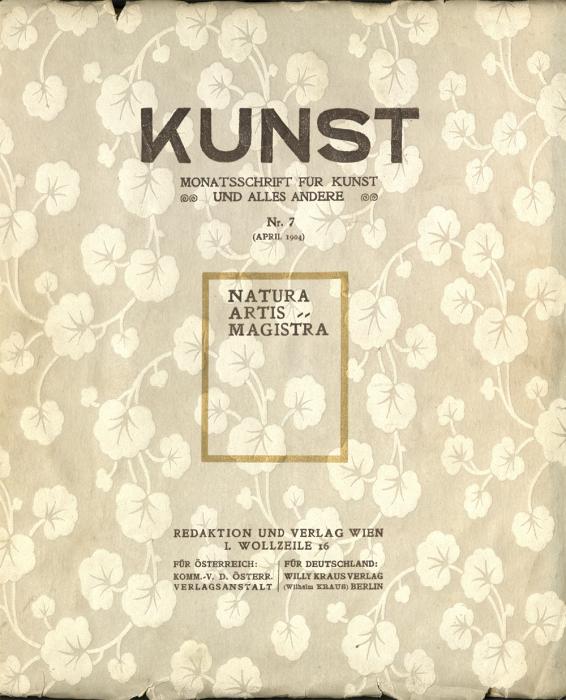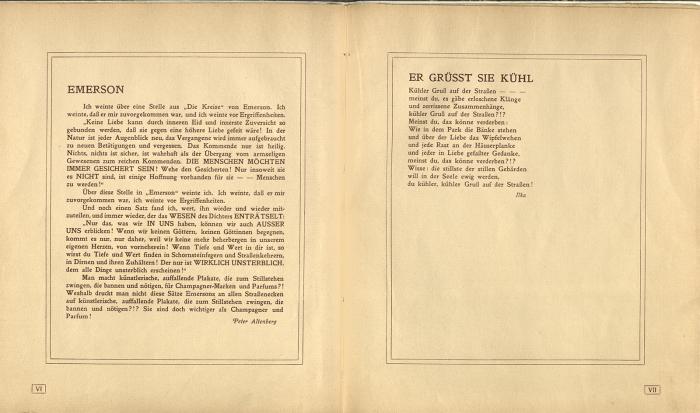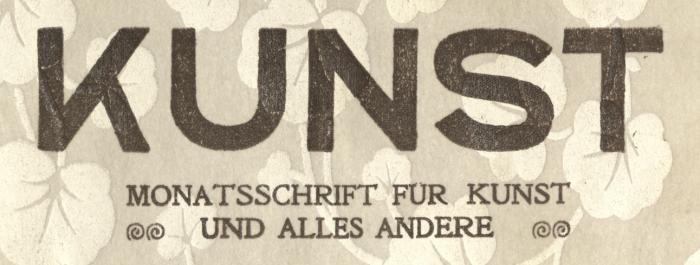
Schriftart KUNST
Weiss jemand, um welche Schrift es sich bei untenstehendem "KUNST"-Schriftzug handelt? (Stammt von einer Wiener Kunstzeitschrift, 1903/1904.) Ich glaube, die Schrift des Untertitels ist eine Garamond? Gibt es ausserdem eine typographische Bezeichnung für diese spiral- bzw. schneckenförmigen Verzierungen links und rechts?
Weiss jemand, um welche Schrift es sich bei untenstehendem "KUNST"-Schriftzug handelt?
Das ist handgemacht. K und S sind derart verunglückt, daß kaum vorstellbar ist, daß eine Gießerei das als Satzschrift produziert hätte. Wenn ich mir den Hintergrund ansehe, tippe ich auf Linol- oder Holzschnitt oder ein ähnliches Verfahren.
Ich glaube, die Schrift des Untertitels ist eine Garamond?
Eher nicht, und wenn, dann eine ganz schlechte. Bei einigen Buchstaben passen die Proportionen gar nicht zur Garamond. Vielleicht ist das auch eine händisch nachgezeichnete oder nachgeschnittene Schrift nach einer Garamond-Vorlage.
Gibt es ausserdem eine typographische Bezeichnung für diese spiral- bzw. schneckenförmigen Verzierungen links und rechts?
Ganz allgemein: Schmuck. Eine konkrete Bezeichnung für diese Form wird es nicht gegeben haben.
Auch wenn ich dem Kollegen Pachulke nur ungern widerspreche: KUNST könnte schon eine Satzschrift sein, so eine jugendstilige (bzw. Art Deco-)-Serifenlose aus der Jahrhundertwende, die in Österreich und auch in Deutschland, Italien, Frankreich damals echt gern genommen wurden. "Secession" oder Secessionsgrotesk hieß mal eine derartige Schrift, wenn ich mich richtig erinnere. Es dürfte einige ähnliche und vielleicht sogar sehr ähnliche digitale Schriften geben ... suche einfach mal unter den Stichworten Art Deco, Jugendstil, Secession - am besten in Verbindung mit Serifenlos und du solltest zumindest bei myfonts was finden.
Recht hat Kollege Pachulke natürlich mit der Bemerkung, dass die Unterzeile niemals eine Garamond ist. Ist vermutlich eine Bleisatzschrift aus der Gießerei Poppelbaum ...
Tatsächlich erinnert der "KUNST"-Schriftzug an gewisse fett gesetzte Jugendstilschriften, ein wenig vielleicht sogar an das Firmenzeichen der Wiener Werkstätte... (Unter MyFonts fand ich die ähnliche Schrift "Chancellor", die sich allerdings angeblich am "Plakatstil" orientiert, der ja dann ein wenig später einsetzte, wenn ich richtig liege; die Zeitschrift "KUNST" stammt von 1903/04.)
Auf die Idee der Garamond kam ich, da in einem Aufsatz zur Zeitschrift steht, die Schrift sei eine "zeitlos schöne Garamond-Antiqua" (vgl. hierzu die abgebildete Seite aus dem Inhalt).
Sehr interessant fand ich die Idee bezüglich Holz-/Linolschnitt: Hierzu ein Bild der ganzen Titelseite, die, wie auf der Rückseite der Zeitschrift angegeben, aus "Relief-Pergamentpapier" bestehen soll... Falls jemand etwas über die angewandte Technik wüsste, wär das ungemein hilfreich!